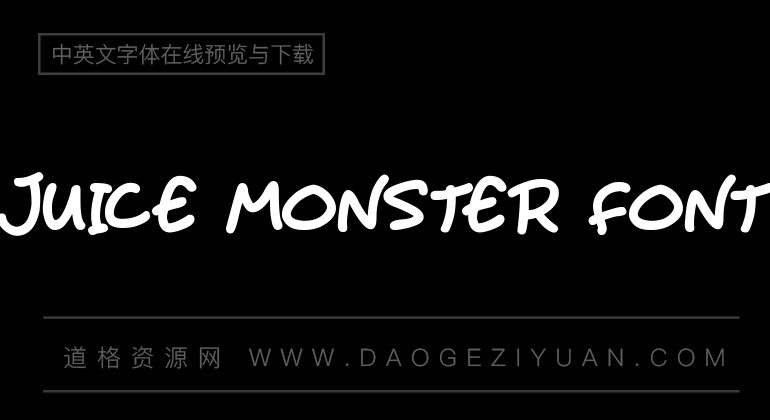
Juice Monster Font 是一种手写风格的字体,其特点是充满活力和趣味性。它由 Hanson Design Studio 设计,可以用于各种设计项目,如海报、标志、印刷品、包装等等。该字体有两种风格,一种是简单的手写字体,另一种是带有插图和装饰性元素的手写字体,使得设计师可以根据需要选择不同的风格。Juice Monster Font 非常适合用于需要展现创意和个性的设计项目。内容介绍
Juice Monster Font是一款非常不错的手写艺术字体,具有很好的视觉感,适合于文化类的宣传设计、商业类品牌的广告和产品包装设计以及个性化文字排版等较多场景。